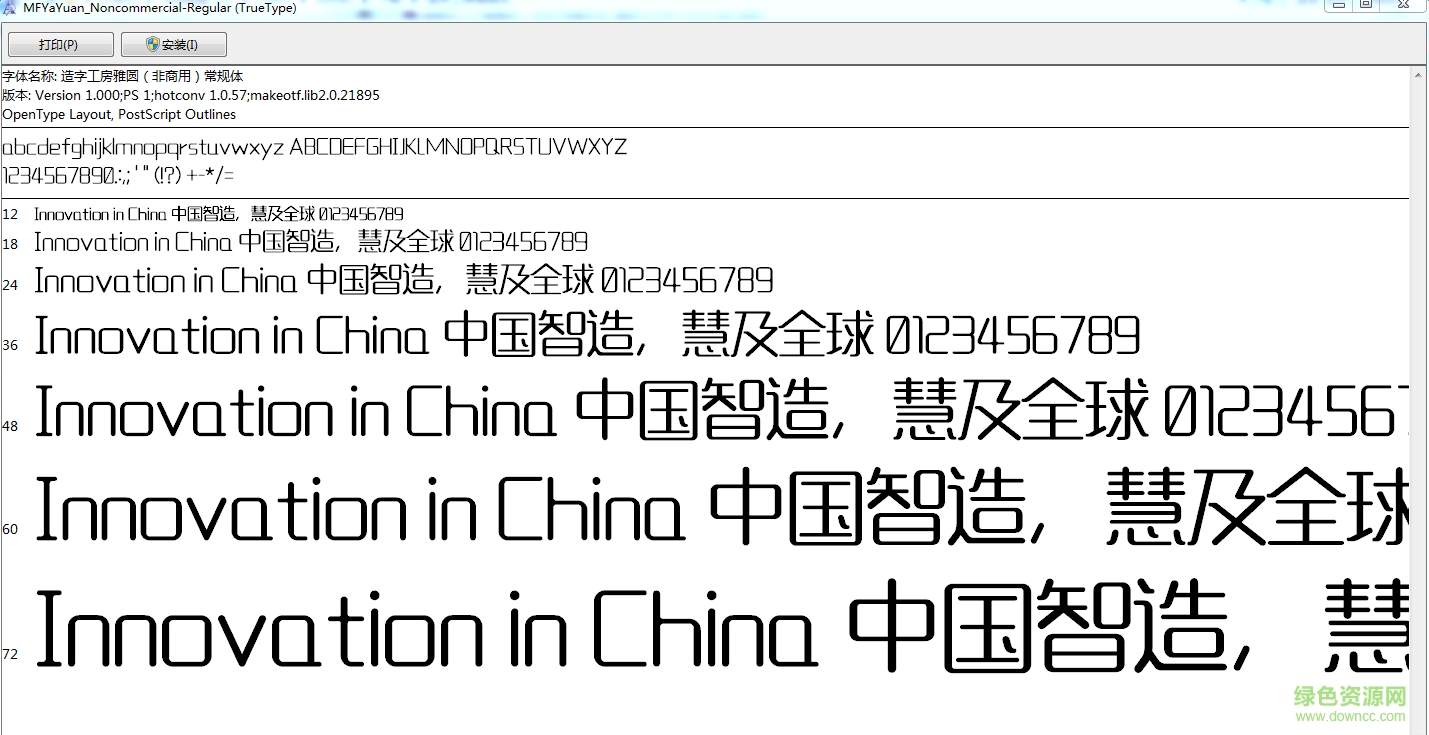
mfyayuan_noncommercial regular
mfyayuan_noncommercial regular(造字工房雅圓非商用常規(guī)體)是一款備受好評的精品藝術(shù)字體,字體曲線變化自然,結(jié)構(gòu)穩(wěn)定,特征鮮明,視覺表現(xiàn)力強,喜歡這款字體的朋友快來下載吧!